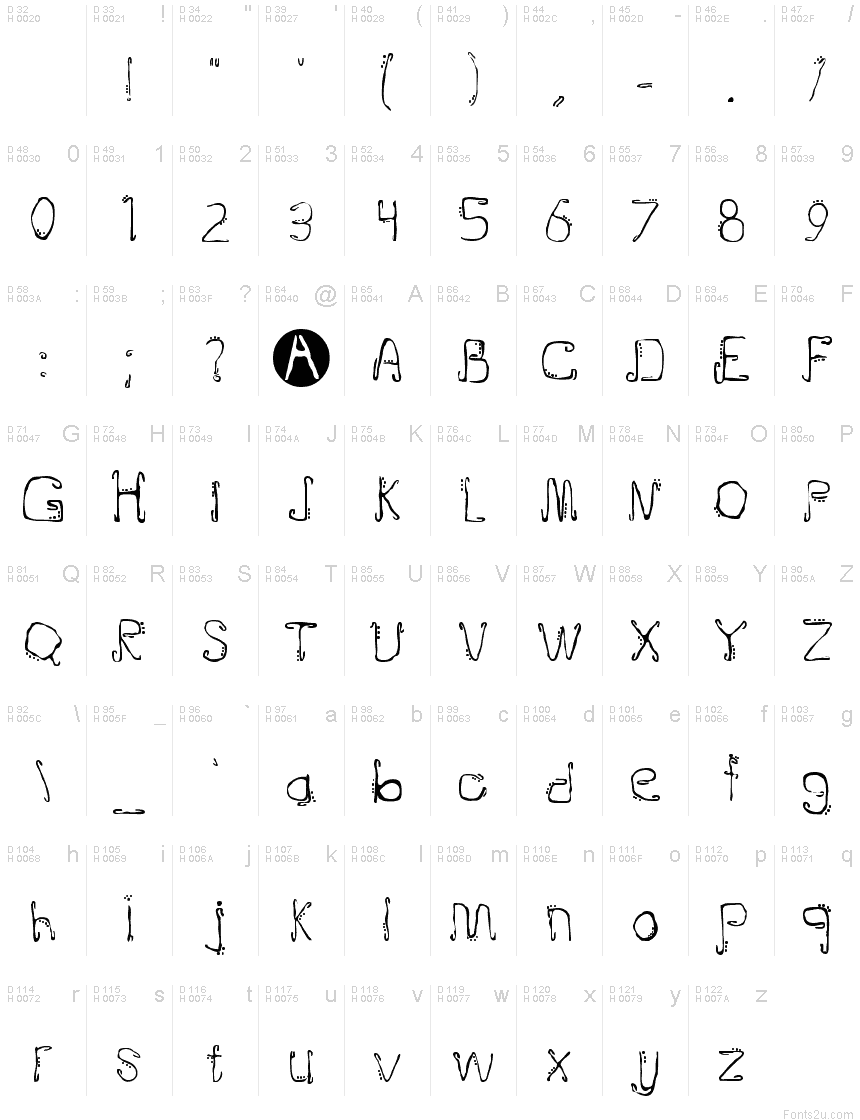
خط Doublejoint من تصميم Ola Nilsson هو خط مزخرف مجاني يتميز بحروف تشبه الأسلاك المرنة المرصعة بمسامير دقيقة. تلتوي الخطوط وتنثني في أماكن غير متوقعة، مما يضفي على الكلمات طاقة حرة ومتموجة، بينما تبدو اللمسات المنقطة كأنها براغي صغيرة أو خرزات انطبعت في الحبر. هذه اللمسة اليدوية الخام تمنح الخط طابعاً مرحاً بعيداً عن التكلف.
مع Doublejoint، ستحصل على طابع جريء وغير تقليدي يبرز بوضوح على ملصقات الحفلات، والمجلات المستقلة، ومنشورات DIY، وشعارات العلامات التجارية المبتكرة، وعناوين الكتب المصورة، ودعوات الحفلات. هذا الخط المجاني يتألق عند استخدامه بأحجام كبيرة لتظهر "المفاصل" المنقطة بوضوح؛ وللنصوص الصغيرة، ادمجه مع خط هندسي بسيط بلا زوائد لضمان سهولة القراءة والتوازن البصري.
خريطة محارف خط Doublejoint